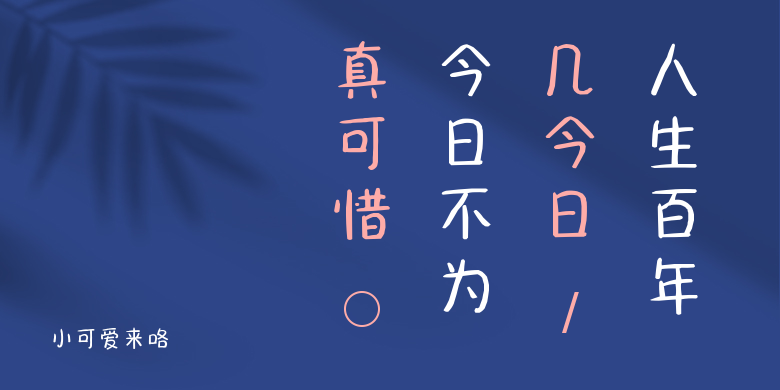
小可爱来咯
小可爱来咯,这款字体结构工整、笔画清晰,兼顾美观与易读性,适用于标题、正文、海报、包装、LOGO 等多种场景。字形优雅稳定,风格百搭耐看,适配日常排版与创意设计,让文字呈现更舒适、更具质感。小可爱来咯一笔一画,皆是细节,以均衡的比例、流畅的线条打造舒适视觉体验,字形端正大气,风格简约现代。无论是商业设计、品牌宣传还是日常排版,都能轻松驾驭,让文字更有格调与力量。小可爱来咯字体下载。